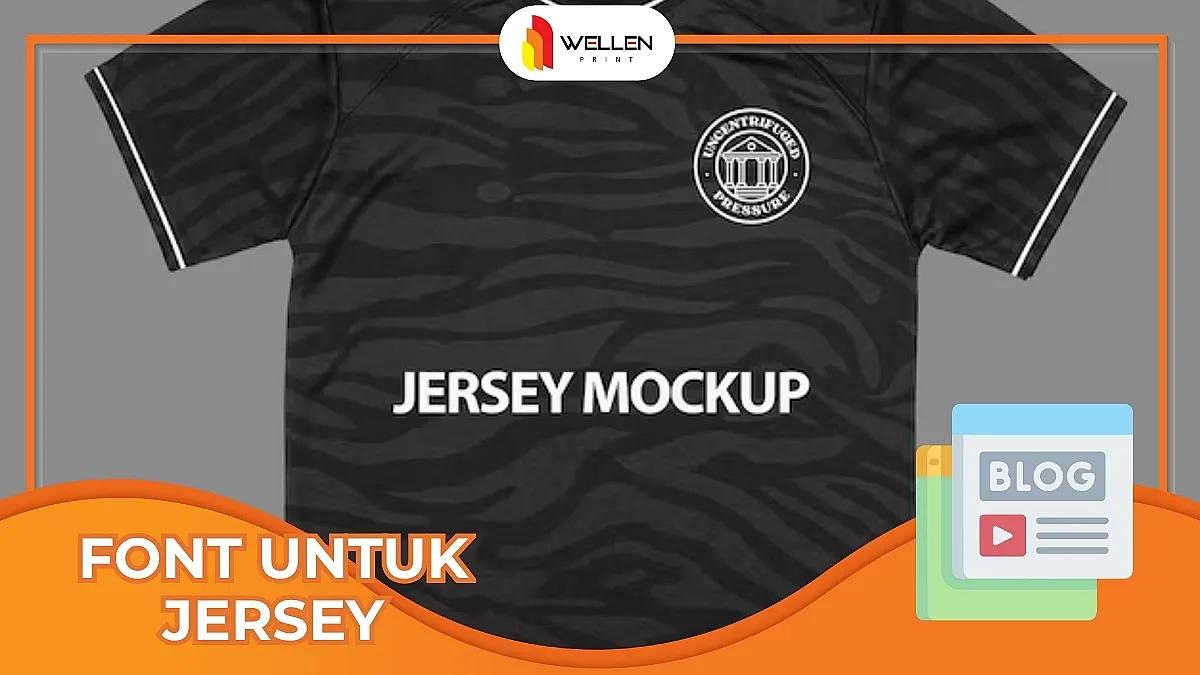
9 Font untuk Jersey: Sporty dan Profesional, Makin Cakep
Salah satu elemen visual dengan peranan krusial terhadap sebuah jersey adalah jenis tipografi untuk mengukir nama dan nomor punggung pemain. Peranannya vital dalam membangun identitas tim dalam persepsi audiens. Selain memenuhi standar estetika, font untuk jersey harus tampak profesional, tegas, dan memiliki keterbacaan (readability) jarak jauh yang baik seperti berikut.
Font bagus untuk jersey ini juga menjadi standar tampilan klasik olahraga Amerika. Ciri khasnya adalah bentuk huruf cenderung kotak (blocky) dengan sudut-sudut dipotong 450 dan tebal. Citra tradisional, kuat, dan loyal terpancar dari penggunaan font ini pada jersey. Paling banyak digunakan untuk jersey baseball atau American football dengan kesan old-school.
Jersey M54 merupakan versi modern dari font Varsity dengan kesan klasik yang kental. Karakteristik utamanya adalah huruf kotak tebal dengan potongan sudut diagonal yang paling cocok sebagai font angka untuk jersey pemain. Pilihan tepat untuk yang tim yang menginginkan tampilan sporty tapi tangguh. Umumnya dipakai jersey olahraga basket, dan bola.
Namun, saat demam esports melanda dunia, font Jersey M54 juga menjadi salah satu favorit lini olahraga digital tersebut. Hal ini dikarenakan kemudahan modifikasi font yang ditawarkan melalui penambahan efek garis tepi (outline), bayangan (shadow), dan lengkungan (warp). Tampilannya bisa jadi lebih futuristik sesuai karakter e-sports, tapi tidak kehilangan karakter aslinya.
Sesuai penamaannya, Collegiate menekankan nuansa prestisius dari akademi dan universitas serta kesan disiplin tinggi. Sebab itu, paling direkomendasikan menjadi pilihan font untuk jersey bola, basket, atau rugby dari klub milik sekolah atau kampus. Tipografi ini sangat mirip dengan font Varsity, dengan dimensi lebih ramping dan garis tepi (outline) lebih kompleks.
Ciri khas lainnya yang membedakan Collegiate dengan font lainnya adalah potongan miring menyerupai oktagon di sudut huruf dan celah kecil di bagian tengahnya sehingga menyerupai cetakan stensil. Modifikasinya juga mudah, bahkan mampu menghasilkan efek 3D dengan sedikit teknik lapisan warna kontras pada garis tepi dan bagian tengahnya.
Rekomendasi font untuk jersey selanjutnya adalah Athletic, yang dari namanya saja sudah lekat dengan bidang olahraga. Karakter font ini adalah memiliki huruf tebal dengan struktur yang kaku, sangat minimalis tapi memancarkan kesan tegas dan tangguh yang kuat. Paling banyak dipakai pada jersey basket dan bisbol, terutama untuk kostum pertandingan besar.
Scoreboard merupakan font unik yang meniru tampilan lampu LED pada papan skor digital stadion. Huruf dan angkanya terbentuk dari titik-titik (dots) atau garis-garis terpisah. Jenis tipografi yang mampu menghidupkan nuansa retro-teknologi era 80-an dan 90-an. Tematik, klasik, tapi tetap memiliki tingkat keterbacaan tinggi karena pola dasarnya mengikuti aturan standar tipografi.
Anda bisa mengaplikasikannya pada berbagai jenis bahan jersey, baik Polyester, Dry Fit, Hyget dan lainnya. Saat ini, bidang olahraga yang paling banyak menggunakan font Scoreboard pada jersey adalah cabang e-sports. Namun, sejatinya tetap memiliki kecocokan tinggi dengan berbagai olahraga lainnya, terutama yang ingin membentuk citra futuristik tapi penuh nostalgia.
Anton adalah nama font untuk jersey futsal dan olahraga lainnya yang memiliki karakteristik huruf menjulang tinggi, tebal, dan jarak (spasi) yang rapat. Bagian dari kelompok Sans-Serif ini sejatinya didesain untuk sektor periklanan agar mudah menarik perhatian, terutama untuk detail informasi panjang. Ketika diaplikasikan pada jersey, membentuk citra pemberani dan kuat.
Impact merupakan salah satu font terpopuler untuk kebutuhan tajuk utama koran dan poster karena mudah menarik perhatian audiens. Sebab, jenis font ini sangat tebal dengan lebar huruf sempit, membuatnya tampak padat dan menonjol. Ketika mengaplikasikannya pada jersey, seperti kaos badminton printing, Impact menciptakan kesan profesional, tangguh, dan disiplin yang tinggi.
Oswald merupakan adaptasi modern Alternate Gothic. Mirip dengan Impact, dengan ketebalan huruf yang lebih ramping. Cocok untuk tim yang menginginkan tampilan modis, contohnya untuk cetak jersey padel club. Selain itu, Oswald membangun citra tangkas dan cepat pada pemain. Bentuk huruf yang proporsional juga membuatnya lebih mudah dikombinasikan dengan aneka desain.
Montserrat Bold memiliki bentuk bulat dengan presisi yang seimbang. Hal ini menciptakan kesan modern dan profesional yang kuat, tapi tetap terasa fresh. Penggunaannya populer di kalangan tim olahraga pendatang baru (newbie) karena tidak menunjukkan sinyal agresif seperti Varsity. Meskipun demikian, font ini sangat mudah terbaca, bahkan dari jarak cukup jauh.
Pemilihan font untuk jersey tidak sesederhana soal selera tim, melainkan berkaitan dengan tampilan dan identitas yang berpengaruh besar terhadap persepsi audiens. Font yang tepat akan membuat jersey tim tampak profesional, sporty, dan mudah terbaca ketika tengah berlaga maupun untuk kebutuhan dokumentasi. Dari Varsity hingga Montserrat Bold merupakan rekomendasi font terbaik.